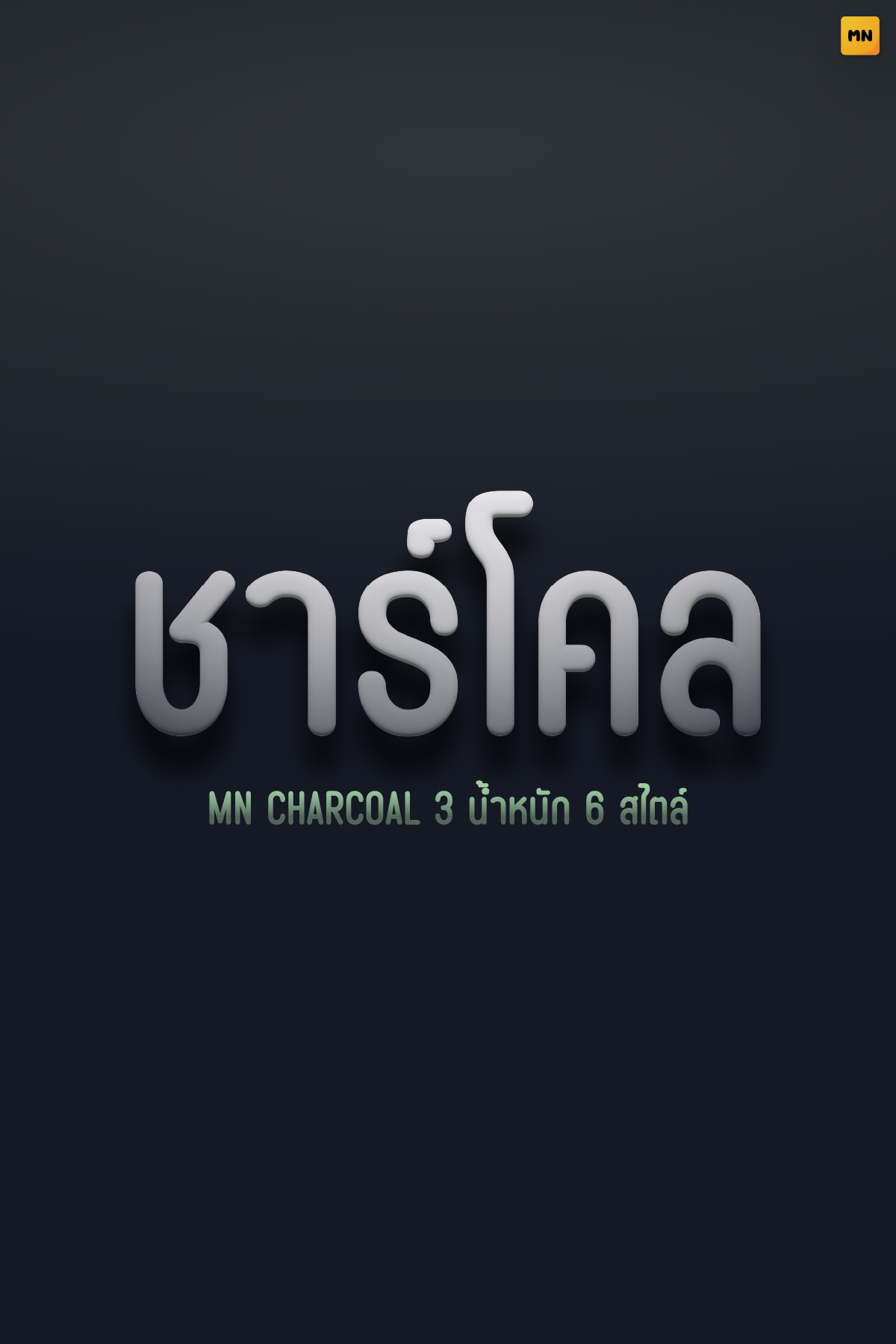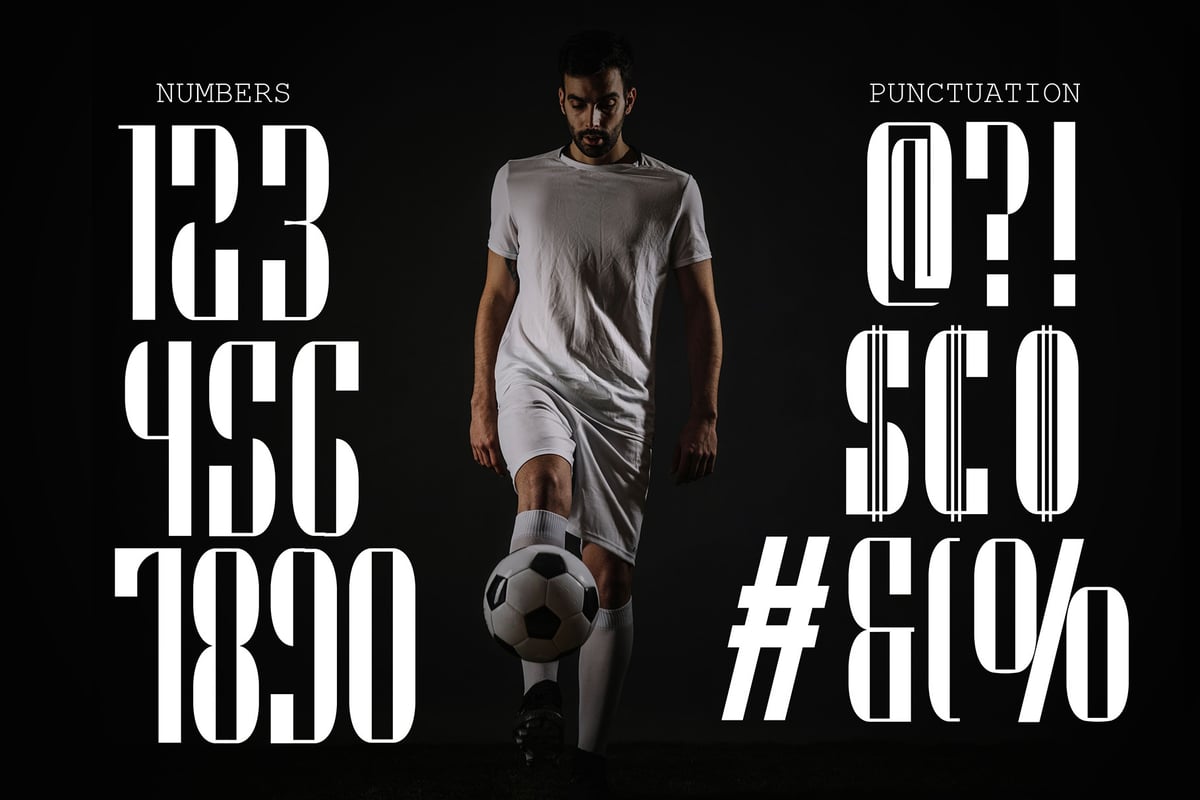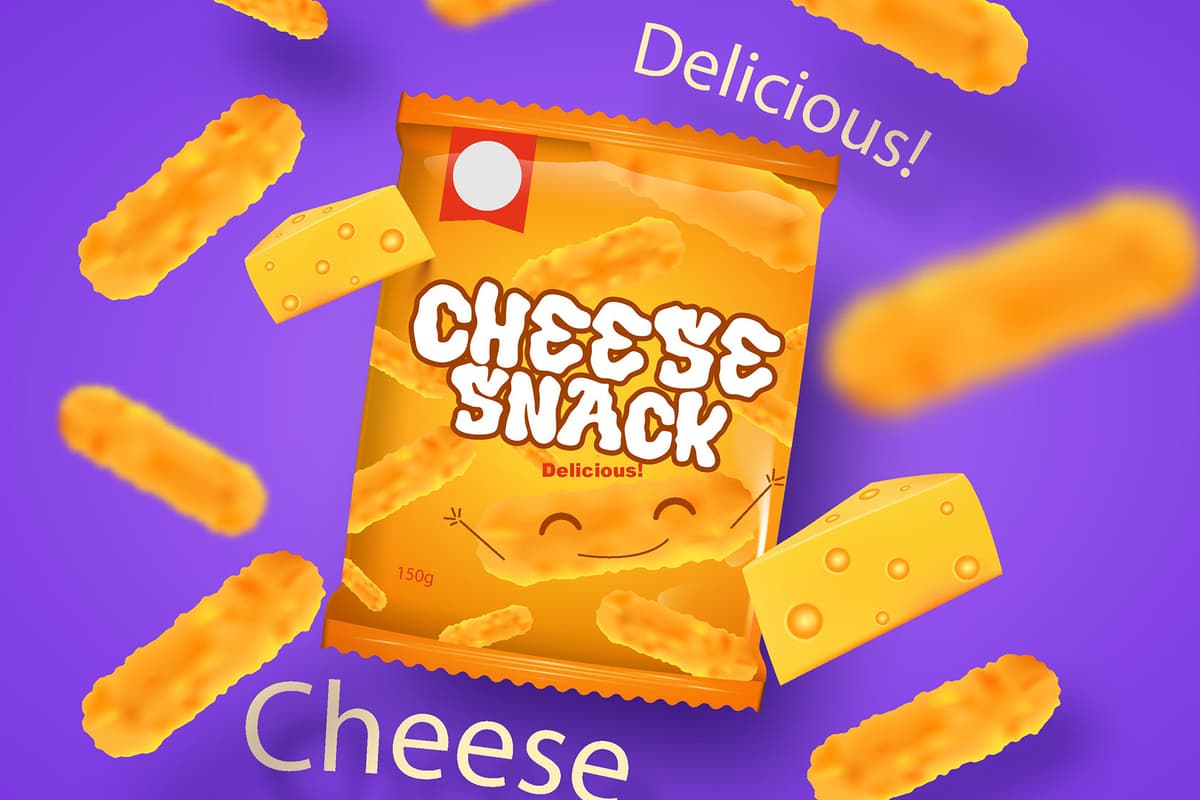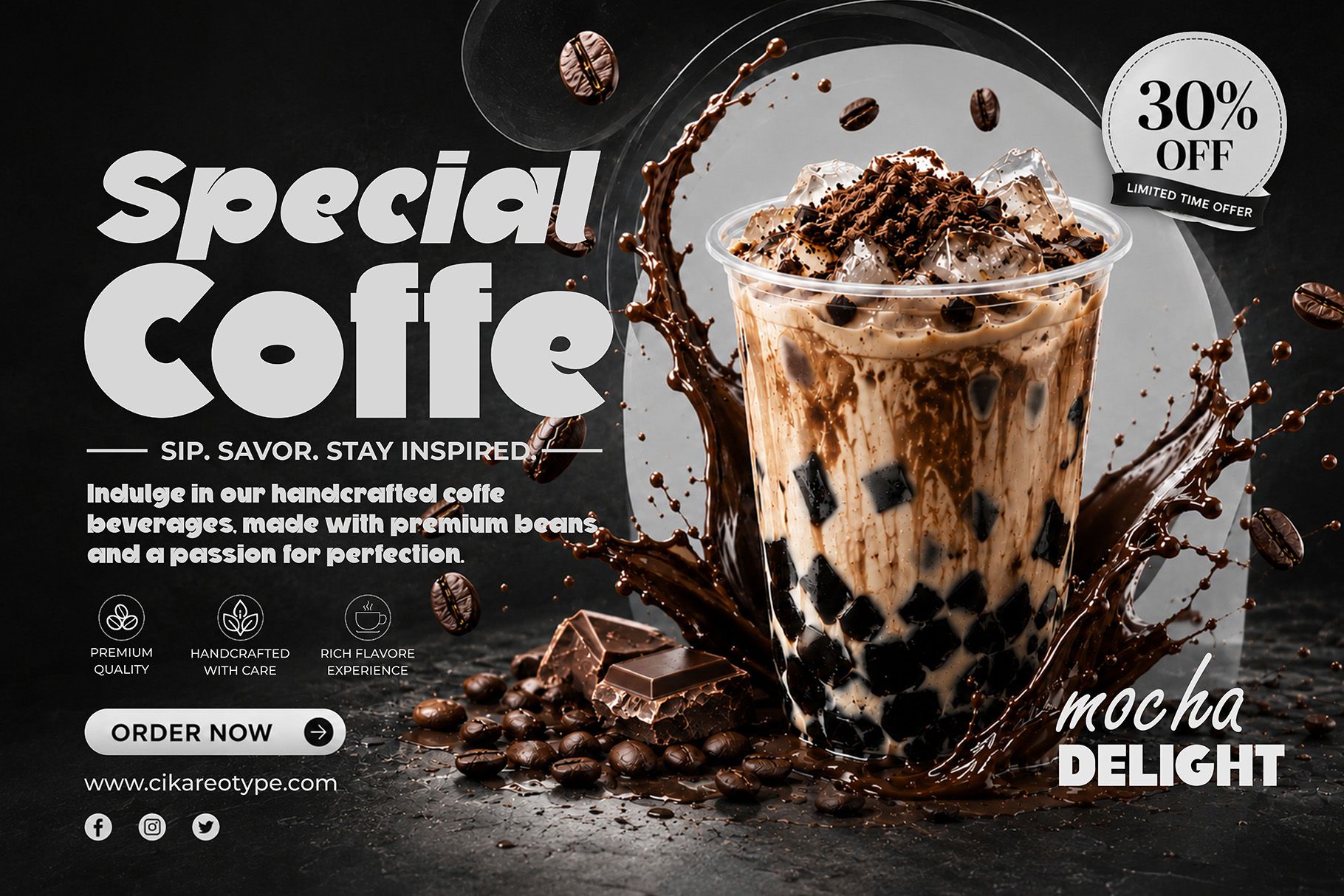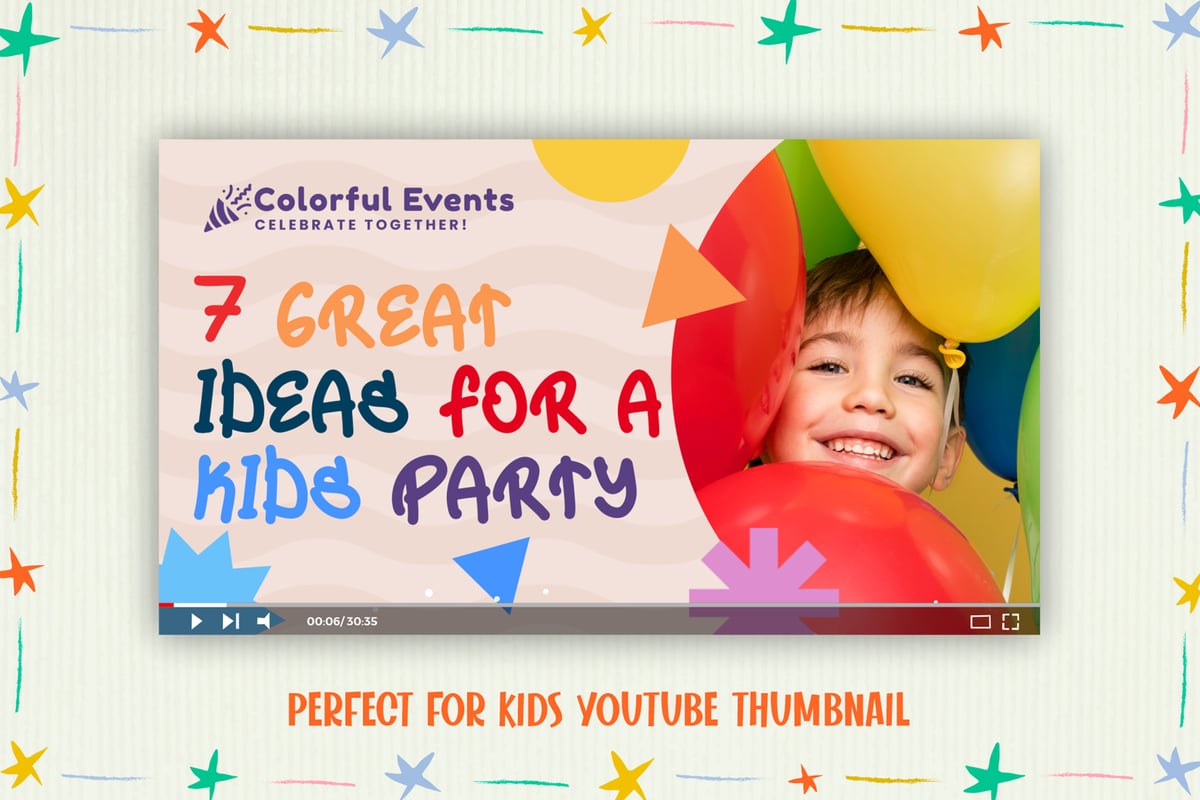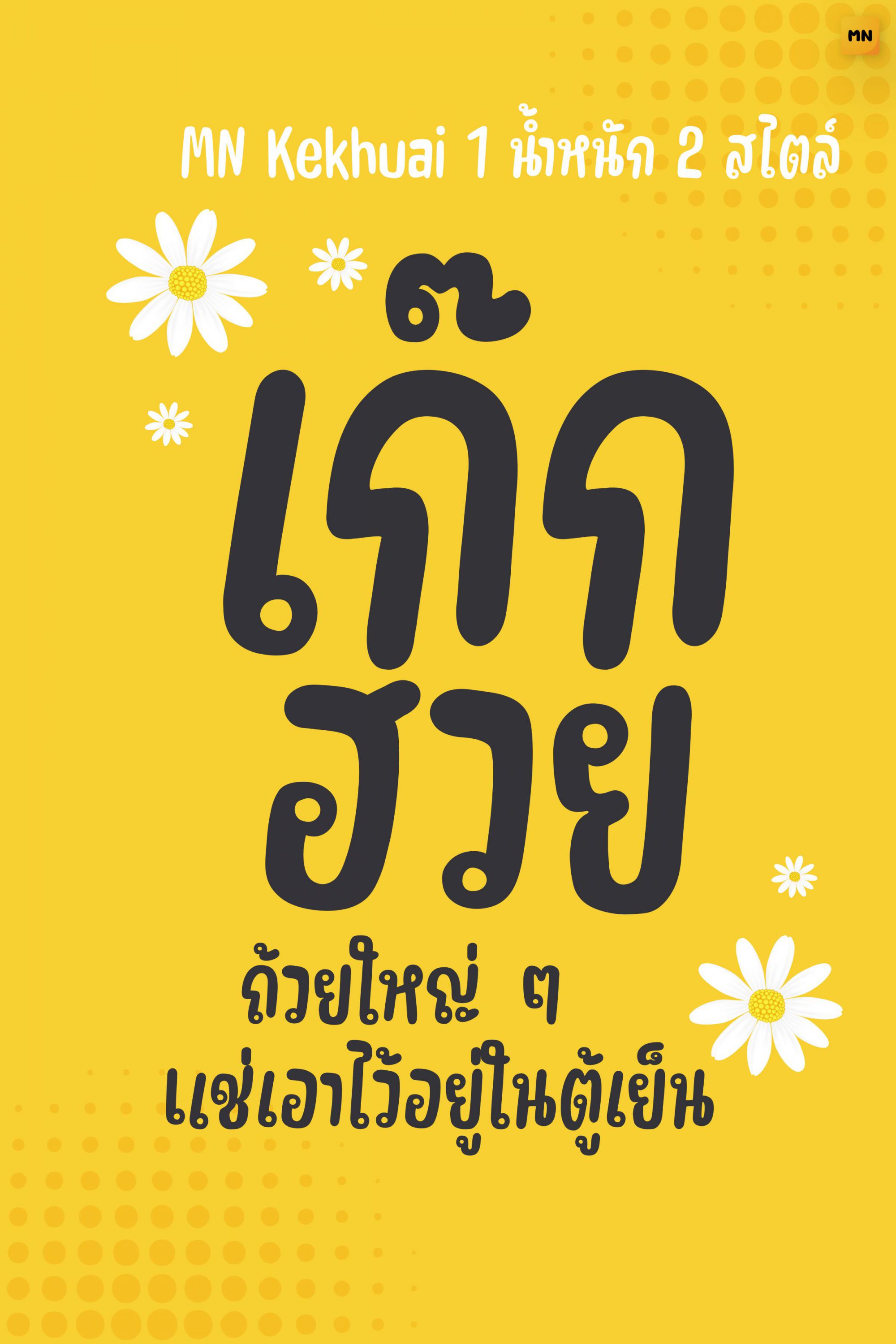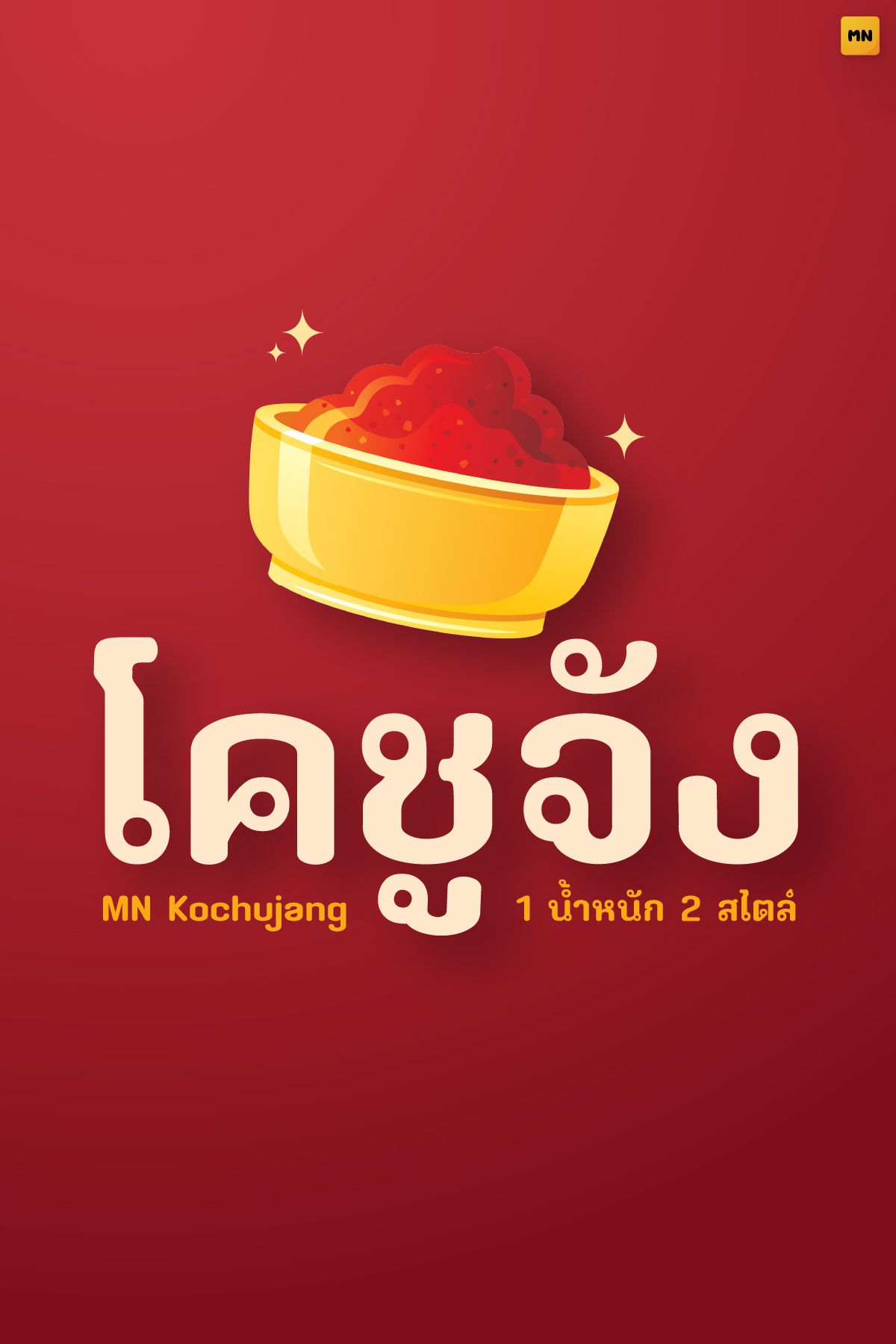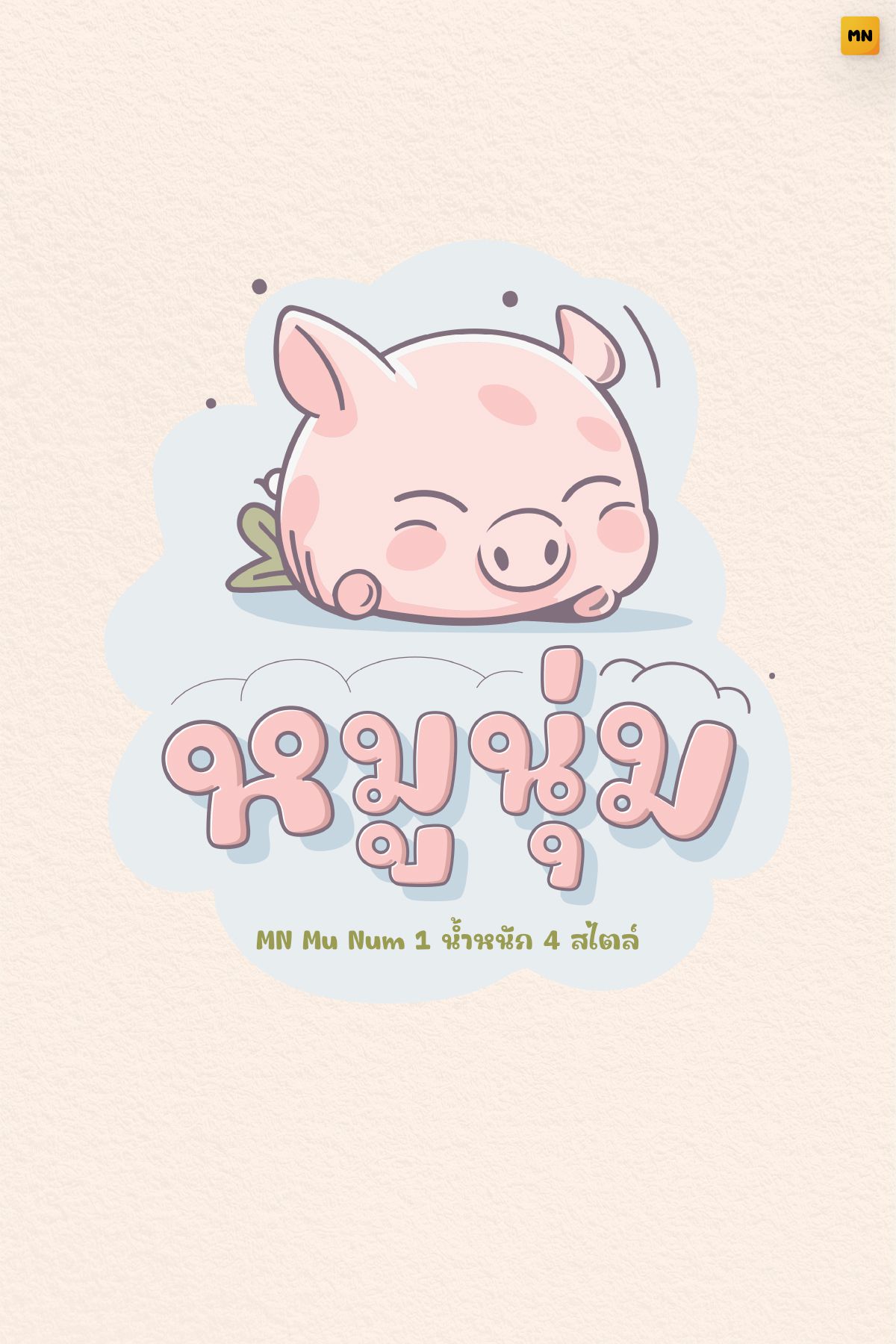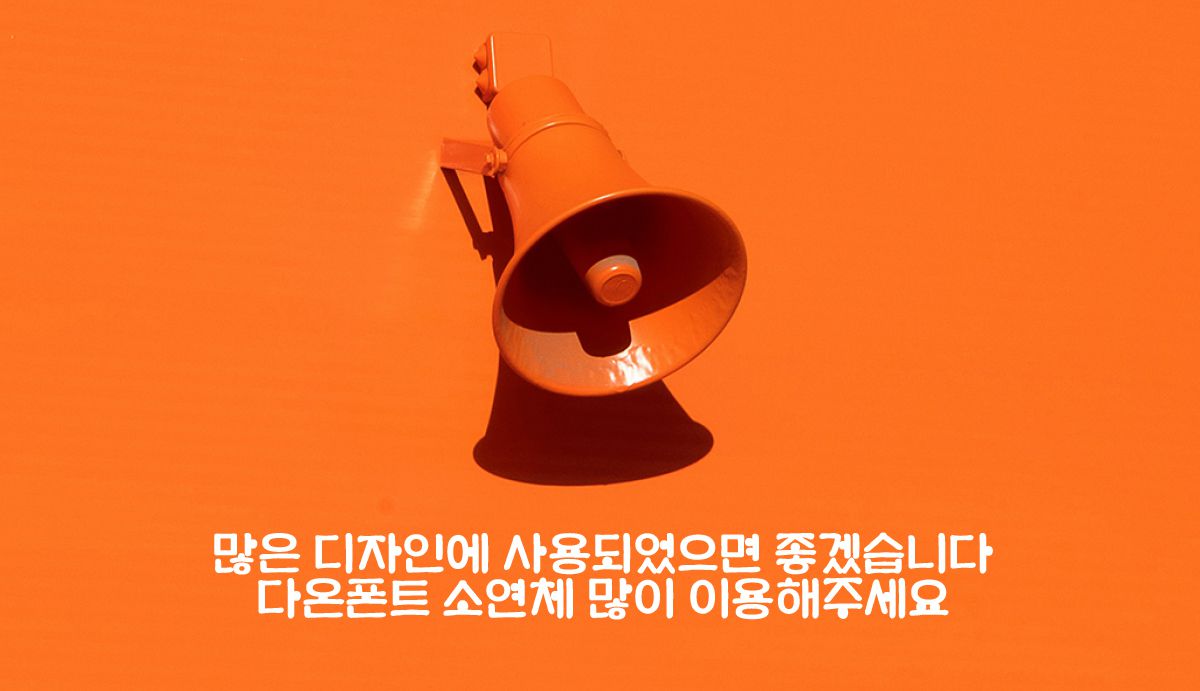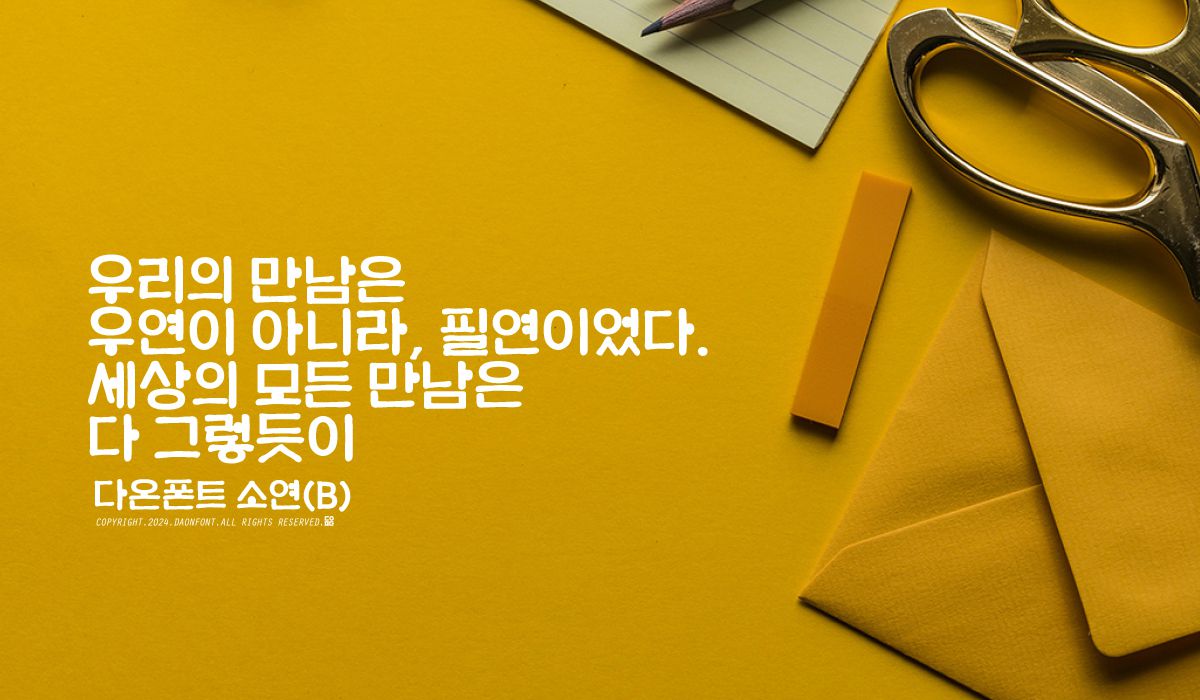
字由引入多家小语种字库,构建覆盖泰文、韩文与阿拉伯文等多语言字体矩阵
近日,字由(HelloFont)宣布,Manee Meefont、DaonFont、NamelaType、Figuree Studio 四家海外字库品牌正式入驻,覆盖泰文、韩文、阿拉伯文及拉丁等多套文字系统,用户可通过字由客户端与官网品牌馆,完成多语言字体的检索、试用、授权与管理。
从中文到世界文字:多语言字体供给长期存在缺口
随着中国企业出海加快,跨境电商、国际文旅传播与多语种内容生产的需求持续增长,非中文字体的使用频率显著上升。然而国内设计师获取泰文、韩文、阿拉伯文等小语种字体时,普遍面临资源分散、渠道不明、授权条款复杂等问题,部分项目甚至因授权不清晰埋下合规风险。
字由此次集中引入四家海外字库,正是针对这一痛点的解法:将分散在不同国家、不同渠道的优质字体资源整合进统一的中文平台,以清晰的授权体系交付用户,填补国内多语言字体资源的供给缺口。
小语种文字美学:覆盖泰文、韩文与阿拉伯文
Manee Meefont(泰国):字里行间的泰式风味
Manee Meefont 是专业泰文字体商店,主打多样的手写风格,从可爱简约到清爽实用一应俱全。其字体已被 Swensen's、MK Restaurants、雀巢、亚洲航空、Traveloka 等品牌实际采用。MN Khop Khun、MN SPAGHETTI、MN MINI 等家族已在字由上线。
图片展示的是泰文“ชาร์โคล”(Charcoal)字样,字体为MN Charcoal 3,有6种风格。背景为深灰色渐变,右上角有“MN”标识。该图片与文档中介绍泰国字体设计公司Manee Meefont的内容相关,是对该公司所设计的泰文字体MN Charcoal 3的展示,体现了其在泰文字体设计方面的成果。 图片展示的是泰文字体“MN Kekhuai”的宣传海报。背景为黄色,上方有白色花朵图案,中间大字“เกิด”和“ฮวง”以粗黑字体呈现,下方小字“ถ่ายใหญ่ ต แซ่บเอาไว้อยู่ในตู้เย็น”以白色字体书写。左上角标注“MN Kekhuai 1 น้ำหนัก 2 สไตล์”。该图片与文档中介绍泰国字体设计公司Manee Meefont的内容相关,展示了其设计的泰文字体样式。 图片展示的是泰文“โคชูจัง”(Kochujang)的字体设计,背景为红色。上方有一个黄色的碗,碗里装着红色的酱料。泰文“โคชูจัง”以白色大字居中呈现,下方用黄色小字标注“MN Kochujang 1 บั้งนัก 2 ไซด์”。右上角有“MN”标识。该图片与文档中介绍泰国字体设计公司Manee Meefont的内容相关,展示了其设计的泰文字体样式。 图片展示的是泰文字体“MN Mu Num 1”的宣传图。画面中,一只粉色的小猪躺在蓝色云朵上,闭眼微笑,显得非常可爱。云朵下方用粉色字体写着“มุนุ่ม”,下方还有“MN Mu Num 1 น้ำหนัก 4 ขนาด”字样。该图片与文档中介绍泰国字体设计公司Manee Meefont的内容相关,直观呈现了其设计的泰文字体风格。
DaonFont(韩国):以当代视角重释韩文结构
DaonFont 是专业的韩国字体设计公司,以当代视角重新诠释韩文(Hangul)的造型特征与结构原理,在品牌设计、出版印刷、数字媒体等场景中实现易读性与视觉平衡的统一。DaonFont 亦具备成熟的定制服务经验,客户涵盖地方政府、公共机构与大型企业。DAON SOYEON、DAON BISANG、DAON JEONGYUL GOTHIC 等已登陆字由。
图片展示了一个橙色背景上放置的扩音器,下方有韩文文字“많은 디자인에 사용되었으면 좋겠습니다 다온폰트 소연체 많이 이용해주세요”,意为“如果能在很多设计中使用,我会很高兴,请多使用多安字体小连体”。图片与上下文紧密相关,上下文介绍了NamelaType是由字体设计师Nur Syamsi创立、总部位于印度尼西亚的独立字体设计工作室,专注为现代视觉传播打造兼具协调美感的拉丁与阿拉伯字母字体,此图可能是该字体设计工作室的宣传图或使用示例。 这张图展示了以亮黄色为背景的视觉内容,左侧有白色韩文文字,文字内容为“우리의 만남은 우연이 아니라, 필연이었다. 세상의 모든 만남은 다 그렇듯이”,下方还有“다온폰트 소연(B)”的字样,同时标注有版权信息。右侧搭配了金属剪刀、黄色便签、信封、铅笔、便签本等文具类物品,整体氛围偏向文艺且贴合字体相关的主题,结合上下文来看,这张图是字由引入多语言字体的相关配图,用于展现字体应用的视觉风格。 图片展示了两款印有韩文的咖啡杯。左侧紫色咖啡杯上印有白色韩文“당신은 사랑받기 위해 태어난 사람”,意为“你是为了被爱而生的”。右侧白色咖啡杯上印有黑色韩文“사랑하는 사람과 함께”,意为“与爱的人在一起”。这两款杯子分别对应文档中介绍的“NamelaType(印度尼西亚):拉丁与阿拉伯文字的协调共生”部分,展示了该字体设计工作室为现代视觉传播打造的兼具协调美感的韩文字体。 图片展示了一本打开的笔记本,左侧页面为红色,右侧页面为蓝色,左侧页面上用白色字体写着“소중한 인연”(珍贵的缘分)。右侧页面上用红色字体写着“감성한글 다온폰트 신서체 소연체 2종이 출시되었습니다”(感性韩文多恩字体新字体小连体2种已发布)。背景为白色,右侧还有两支铅笔和一个粉色花瓶。此图与文档中介绍韩国字体设计公司Jaanfont推出新字体的内容相关,展示了新字体的呈现效果。
NamelaType(印度尼西亚):拉丁与阿拉伯文字的协调共生
NamelaType 是由字体设计师 Nur Syamsi 创立、总部位于印度尼西亚的独立字体设计工作室,专注为现代视觉传播打造兼具协调美感的拉丁与阿拉伯字母字体。创始人 2022 年成为 Google Fonts 字体 Marhey 的贡献者,2025 年获 Al-Burda Award 阿拉伯字体第二名及富查伊拉国际书法比赛阿拉伯字体鼓励奖。代表作包括 Madani、Mahameru、Qamari Sans 等,Kibtah、Ghadir、Qamari Sans Arabic 等已在字由上线。
图片展示了字由上线的多款阿拉伯文字体应用案例。左上角是印有“واطيف”阿拉伯文的T恤,左下角是“برقال”品牌包装,右上角是“الهندية”巧克力包装,右下角是“الهندية”巧克力包装的背面。这些案例体现了字由阿拉伯文字体在服装、食品包装等领域的实际应用,与文档中介绍字由上线阿拉伯文字体的内容相契合,直观呈现了字体的使用效果。 图片展示的是阿拉伯文书法字体,背景为蓝色,配有白云、纸飞机、风筝等图案。图片左侧从上至下依次列出字体风格:Bold、SemiBold、Medium、Regular、Light。右侧对应阿拉伯文内容,分别是“خذ من مرح الأطفال”(从孩子们的欢乐中)、“وهدوء المسنين”(从老年人的宁静中)、“وتواضع العظماء”(从伟人的谦逊中)、“وأحلام الفقراء”(从穷人的梦想中)、“وستعرف معنى الحياة”(你会明白生活的意义)。该图片与上下文介绍阿拉伯文书法字体相关,直观呈现了不同风格的阿拉伯文书法字体及其对应含义。 图片展示了三张风格独特的海报。左侧海报以粉红、白色为主色调,写着“A BLES-SING IN DIS-GUISE”;中间海报以黑色为底,白色大字“OF”和黄色“FRESH AIR”突出;右侧海报以黑色为底,白色大字“EVERY CLOUD”和蓝色“SILVER LINING”醒目。这些海报设计色彩鲜明,文字排列富有艺术感,与上下文介绍的字由引入多家小语种字库,构建多语言字体矩阵的内容相呼应,展示了其字体设计的多样性和美感。 这张图片展示的是阿拉伯文字内容,上方用醒目的黄色字体写着“كن شريفاً أميناً”,下方配有蓝色横线装饰,再下方是两行白色阿拉伯文,背景为带有城市夜景的暗色调画面。该阿拉伯文内容应为相关阿拉伯字体相关创作的配图,与文档中介绍的阿拉伯字体领域创作者、阿拉伯字体奖项及已上线阿拉伯字体的内容相契合,直观体现了阿拉伯字体的应用场景,辅助展现字由覆盖阿拉伯文等多语言字体矩阵的相关内容。
Figuree Studio:面向创意行业的表现力字体
Figuree Studio 是独立字体工坊与创意设计工作室,主打美术字体、品牌用字、手写字体及实验性字体研发。其作品风格鲜明、表现力突出,广泛应用于品牌视觉、包装设计、社媒与文娱内容,尤其契合社媒内容制作与视频剪辑、品牌视觉识别、周边文创及数字产品设计等场景。Deranios、Great Splash、Urban Clash、Astron Kidos 等已可在字由使用。
这张图片展示了一款表现力突出的创意字体,该字体分为数字和标点两类,左侧标注“NUMBERS”,呈现的字体数字包含1、2、3、4、5、6、7、8、9、0等字符,右侧标注“PUNCTUATION”,呈现的字体标点包含@、?、!、$、&、#、%等字符。图片中间是身着白色运动服饰的男子,脚踩足球,这款字体契合创意行业的设计使用需求,可应用于社媒内容、品牌视觉、文创设计等场景,属于字由引入的多语言字体矩阵中Figuree Studio相关的字体样式。 图片展示了一包奶酪零食的包装设计。包装袋为橙黄色,上面有“CHEESE SNACK”字样,旁边绘有笑脸和奶酪图案,还标注了“Delicious!”及“150g”。背景为紫色,周围散布着多块奶酪和零食,营造出丰富的视觉效果。图片与上下文的关系是,通过展示奶酪零食的包装设计,直观呈现字由字库在品牌视觉、包装设计等场景的应用,契合其面向创意行业的字体使用场景。 图片是一则咖啡饮品广告,背景为深色,中央突出展示一杯带有珍珠的摩卡咖啡,咖啡液中加入巧克力块,周围有飞溅的咖啡液和咖啡豆。左侧大字“Special Coffee”下有“SIP. SAVOR. STAY INSPIRED.”及“Indulge in our handcrafted coffee beverages, made with premium beans, and a passion for perfection.”等文字。右上角有“30% OFF LIMITED TIME OFFER”字样,底部有“ORDER NOW”按钮及网址“www.cikareotype.com”,还有社交媒体图标。该图片与文档中介绍字由字库涵盖多语言字体,如泰文、韩文与阿拉伯文,以及字库作品应用于品牌视觉等内容相关,展示了字由字库在饮品广告中的应用。 这张图片是一张儿童派对主题的YouTube缩略图,核心内容为“7 GREAT IDEAS FOR A KIDS PARTY”的醒目彩色文字,文字左侧还有“Colorful Events CELEBRATE TOGETHER”的标识。图片里包含气球和孩童的元素,搭配多彩几何装饰,整体风格活泼,底部标注“PERFECT FOR KIDS YOUTUBE THUMBNAIL”,契合面向创意行业的活泼风格设计,符合多场景视觉使用的需求。
而对文化传播而言,文字是文化最基础的载体。泰文书写的灵动、韩文结构的理性、阿拉伯文书法的韵律,正通过一个个商业与设计项目被更广泛地看见。让不同文字系统的美学在同一平台上被呈现与使用,本身就是一种跨文化交流。